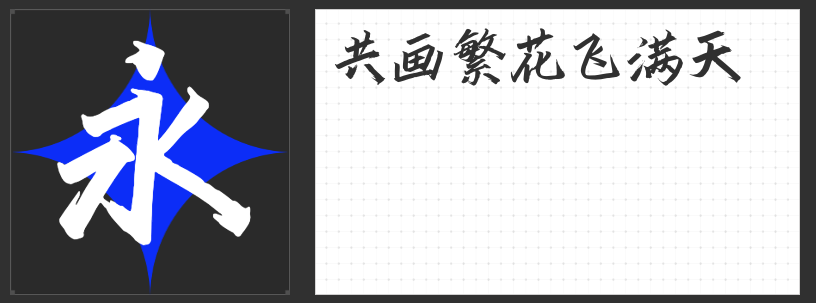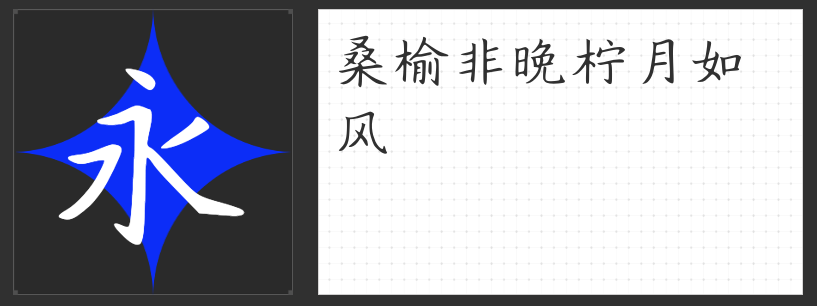
墨韵天成:四款毛笔字体解锁设计中的东方美学
毛笔字体的独特魅力,在于其以笔墨为媒介,将书写者的气韵、力道与情感凝练于字形之中。在当代设计中,毛笔字体不仅是传统文化的符号载体,更能通过其动态美感与力量感赋予作品鲜活的生命力。以下四款各具特色的毛笔字体,以不同的笔法语言与结构美学,为设计注入东方哲学的诗意表达。
一、造字侠今朝醉简
以“醉酒”为灵感,这款毛笔楷书字体突破了传统楷书的工整框架,收笔处凌厉的飞白如刀锋出鞘,笔势酣畅如泼墨挥毫。其正统笔法中暗藏狂放,劲健雄浑的线条既保留了楷书的骨力,又通过墨色浓淡与笔画粗细的对比,传递出一种不羁的洒脱感。这种矛盾张力使其成为白酒包装、文化类海报等场景的理想选择,以字载酒,以墨传情。
二、云书法家韩进水魏碑简繁
取法魏碑的扁方形结构,这款字体通过撇捺的舒展与收笔的顿挫,构建出一种“稳如泰山”的视觉张力。粗细对比强烈的笔画与抬锋细节,既强化了字形的厚重感,又通过动态笔触打破规则的沉闷。其稳健中透出的飞扬气质,使它既能驾驭传统牌匾、古籍封面等场景,也能为现代品牌标识注入历史沉淀的厚重美学。
三、万人字造踏歌行体
以“踏歌而行”的韵律感为设计内核,这款字体在方整严谨的结体中融入圆润笔触与斑驳墨痕,仿佛古卷中走出的活字。其笔画布局匀称却暗藏动势,蓄势待发的力量感与古法用笔的细节相得益彰。这种“以古为新”的设计哲学,使其在文化创意产品、艺术展览海报等领域展现出独特的叙事能力。
四、造字侠醉春风简繁 苍劲
不同于传统毛笔字体的端庄,这款字体以“春风”为意象,通过圆润点画与自然过渡的粗细变化,营造出一种自由率真的灵动感。单字结构周正却不失灵动,笔画走势如春风拂柳,既保留了毛笔书写的自然韵律,又以现代审美重构了传统字形的空间关系,适合年轻化品牌、文创产品等充满活力的设计场景。
毛笔字体的设计价值,在于其以笔墨为语言,讲述超越文字本身的故事。这四款字体或豪放、或厚重、或古朴、或灵动,以不同的笔法哲学与结构美学,为设计提供了丰富的东方美学解决方案。无论是传递文化底蕴,还是塑造品牌个性,它们都能以墨色晕染出独一无二的视觉意境。